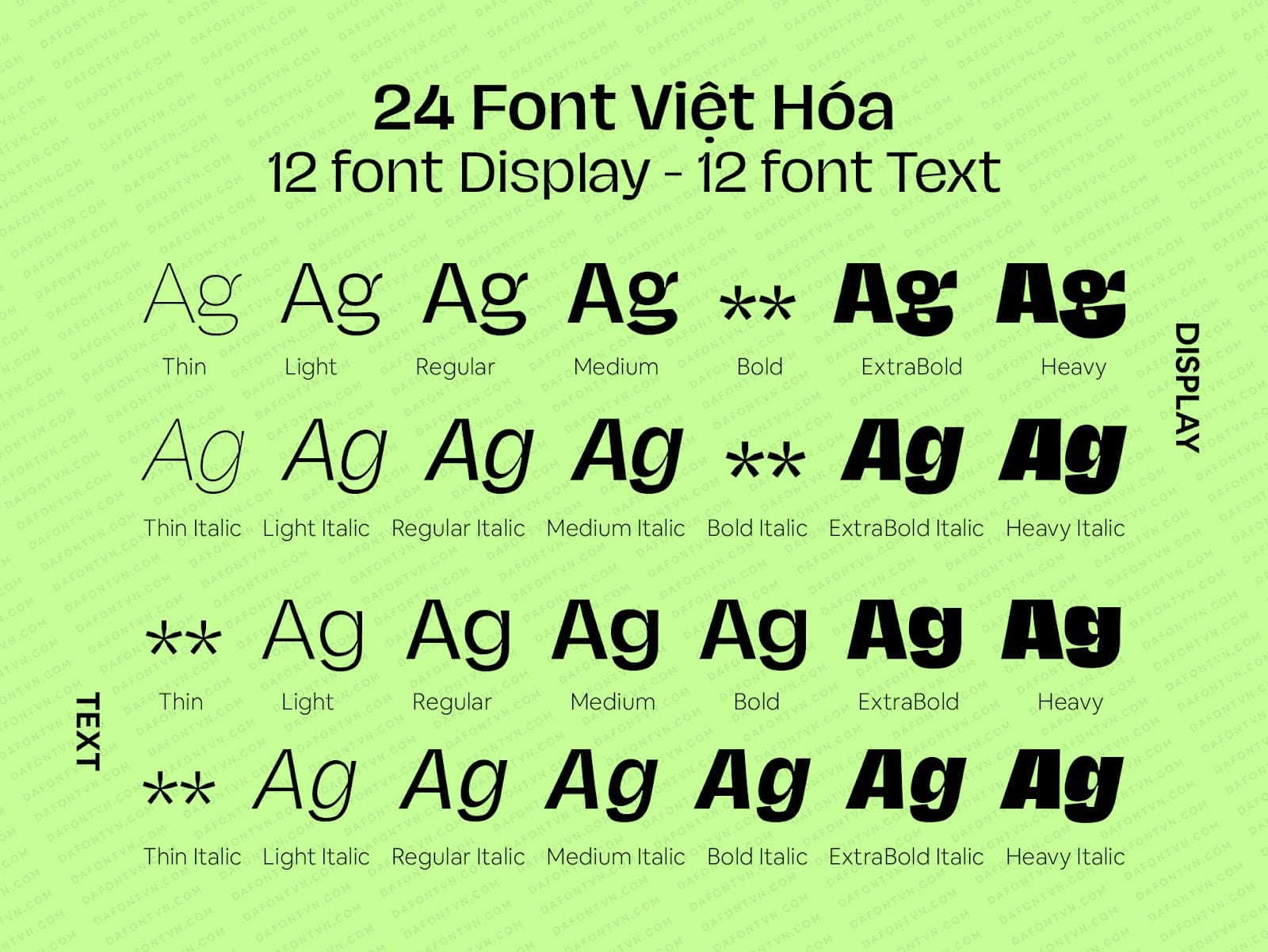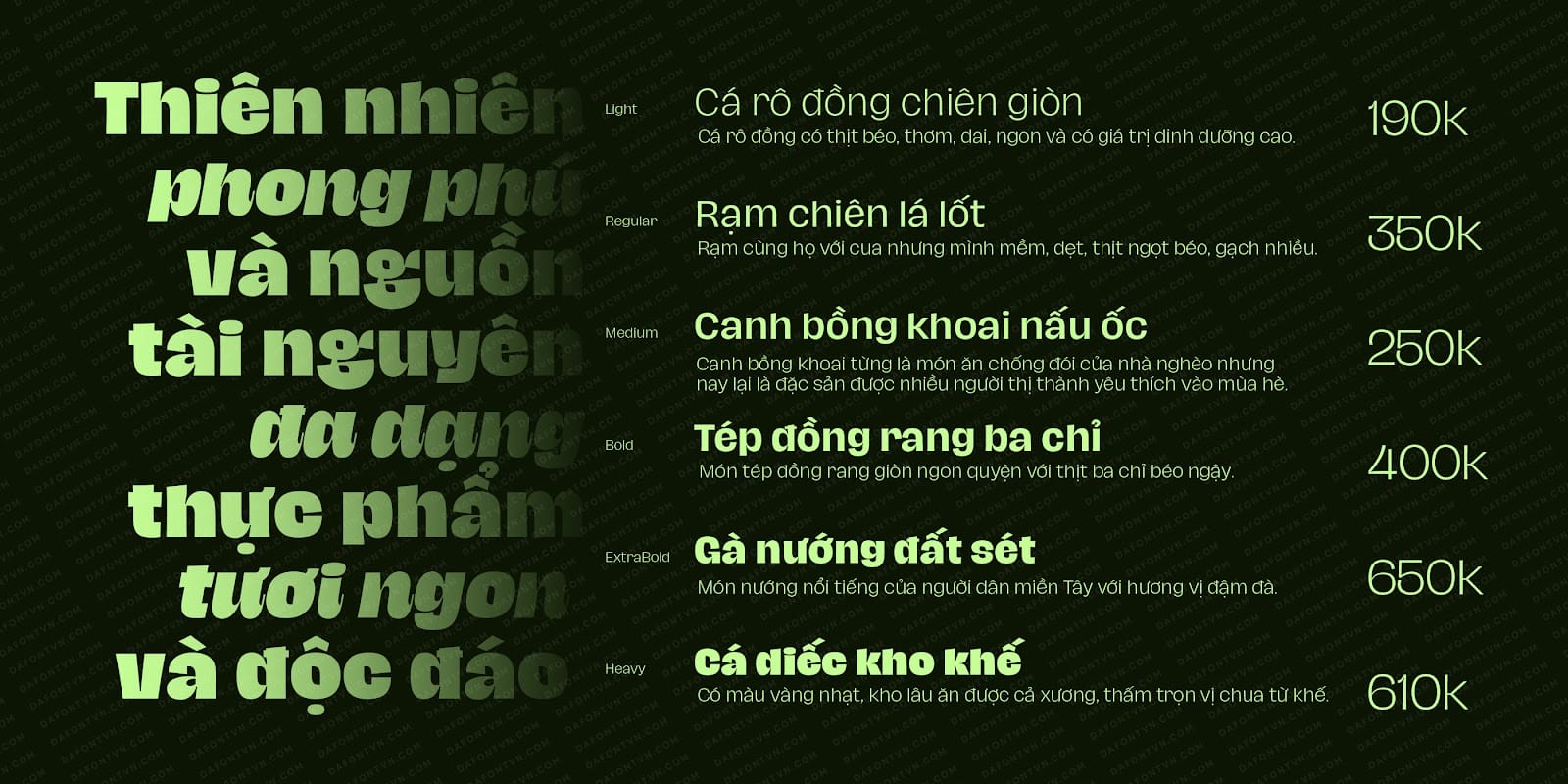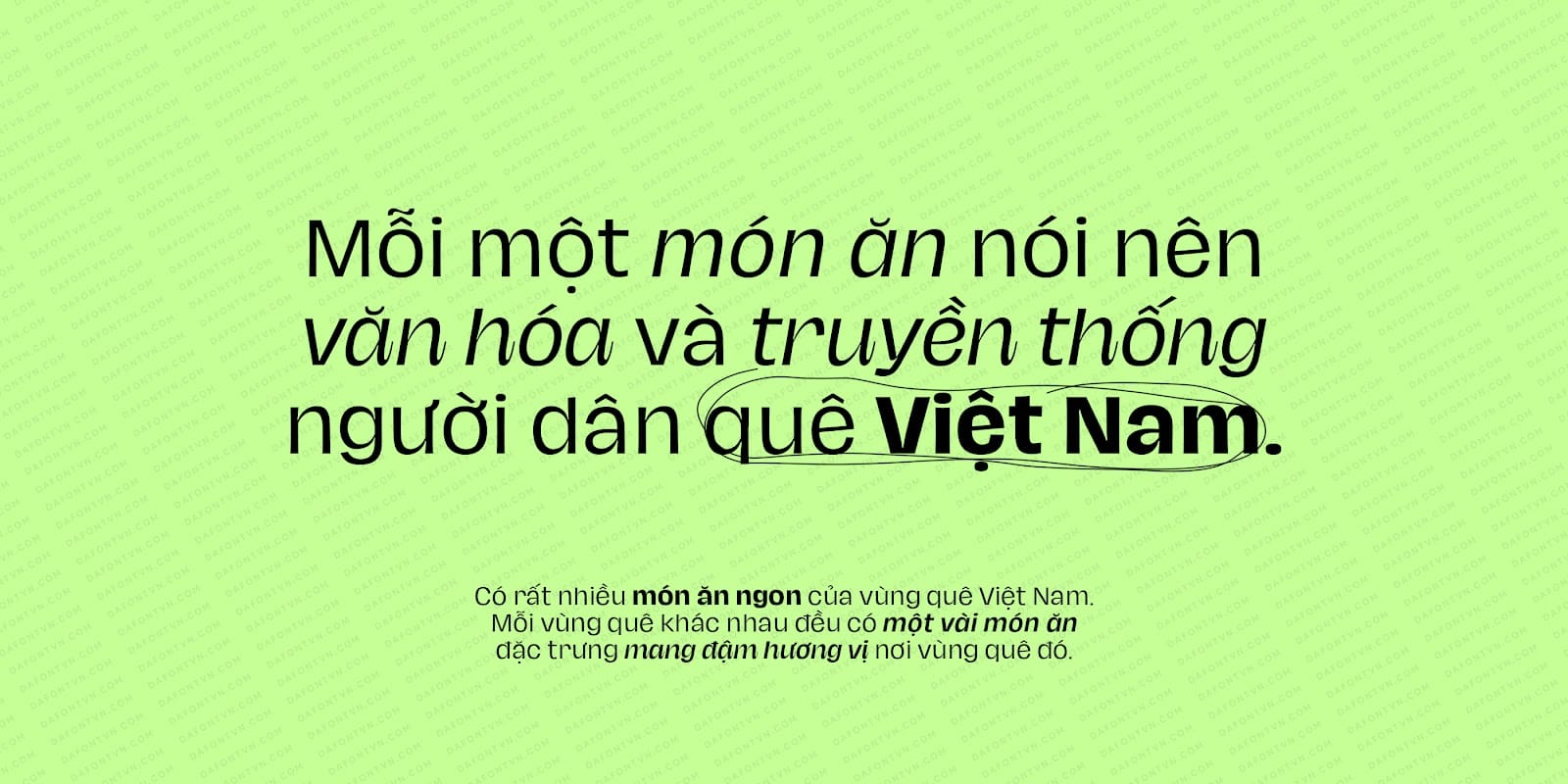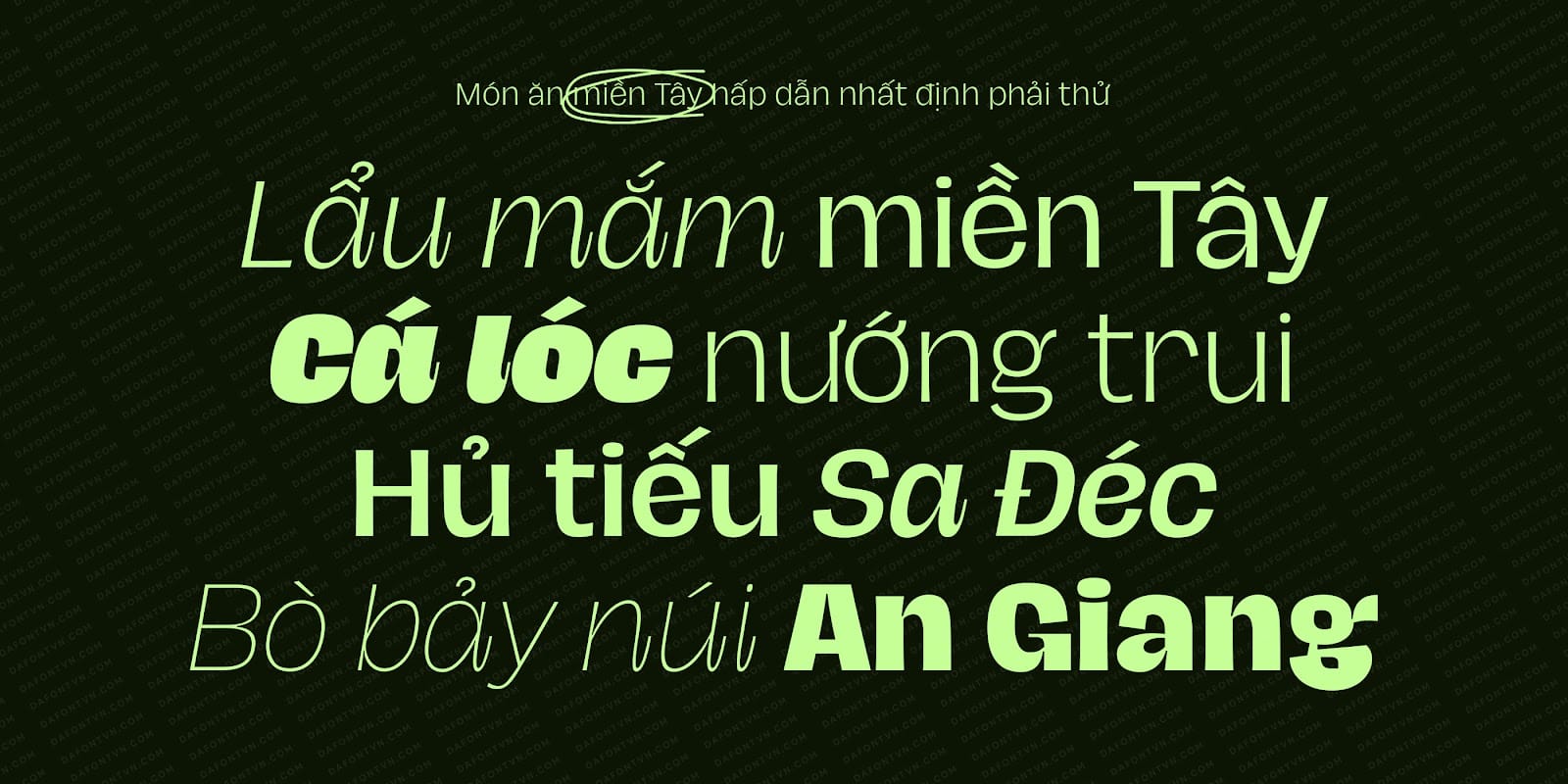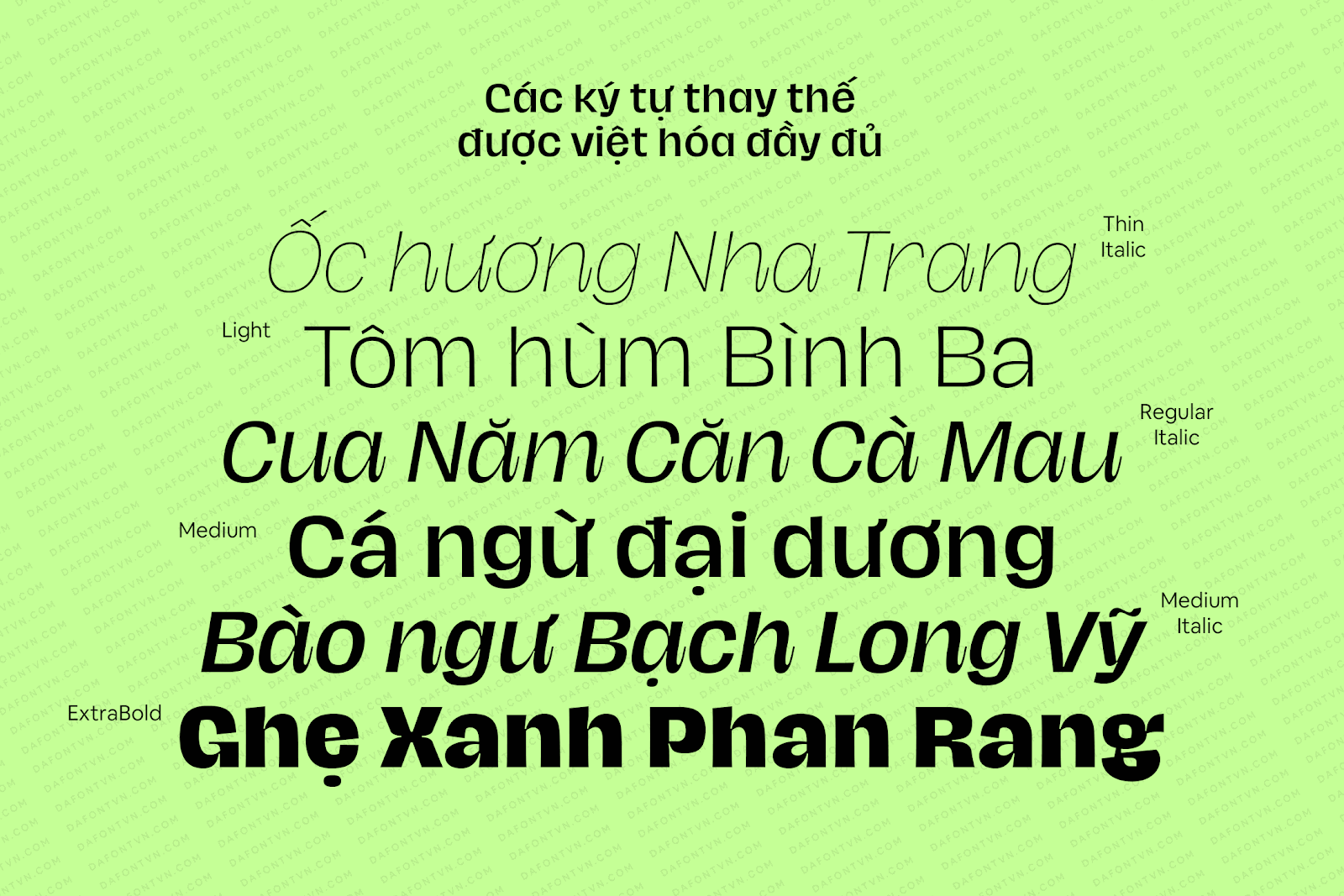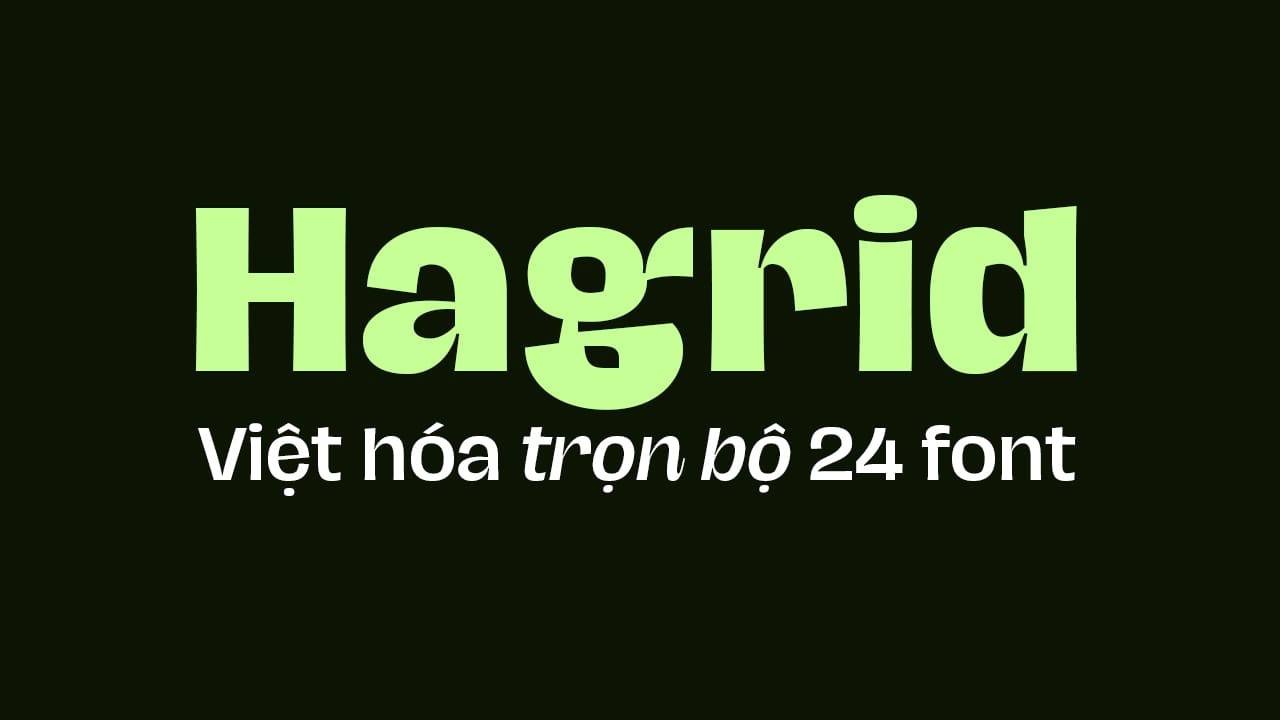
Hagrid Font Family kiểu chữ mật mã (Crypto-typography), nhà thiết kế Cosimo Lorenzo Pancini đã tạo ra kiểu chữ độc đáo này và đặt tên là Hagrid theo tên người khổng lồ được RK Rowling mô tả trong sách Harry Potter.
Hagrid là một bộ font chữ được thiết kế cho việc sử dụng trong biên tập và trình bày, mang đến sự linh hoạt cho trang in và trang số nhờ vào sự tương phản cực cao và những chi tiết độc đáo của nó. Hagrid bao gồm 24 kiểu trong đó 12 kiểu text, 12 kiểu display. Với 6 kiểu đứng và 6 kiểu nghiêng.
Để dễ đọc hơn ở kích thước nhỏ và trên web, phiên bản text đã được phát triển, với lựa chọn trọng lượng hơi khác, kiểu chữ rộng hơn và các điều chỉnh tinh tế để duy trì tính linh hoạt của thiết kế mà không làm giảm tính dễ đọc. Điều này được thể hiện rõ trong thiết kế chữ nghiêng: trong khi chữ nghiêng hiển thị mang lại cảm giác chữ với các đầu cuối thư pháp, thì thiết kế văn bản lại hạn chế hơn, với kiểu dáng nghiêng cổ điển hơn và hình dáng grotesque hình học.
Ngoài ra, bộ font còn bao gồm các tính năng của OpenType và bộ phong cách thay thế đều được tối ưu, chỉnh sửa và việt hóa đầy đủ, các bạn có thể sử dụng nó dễ dàng trên PTS, AI…